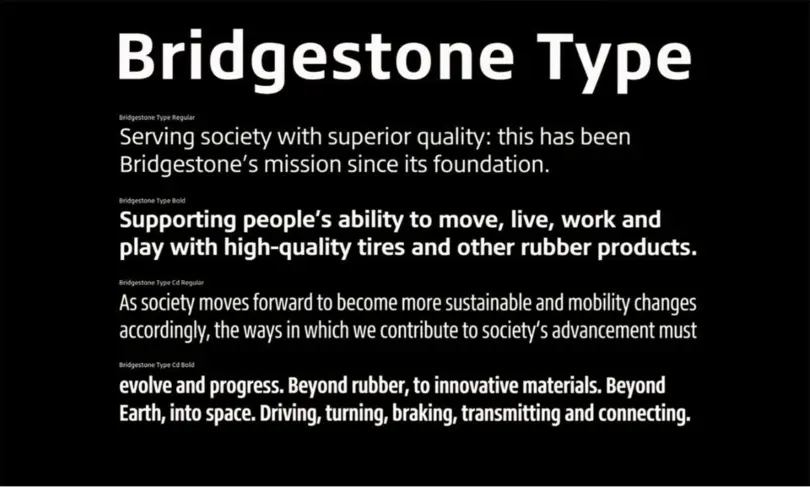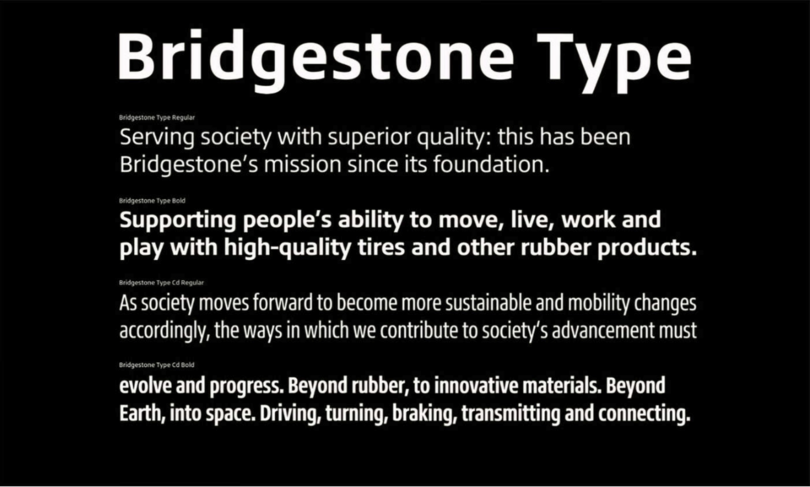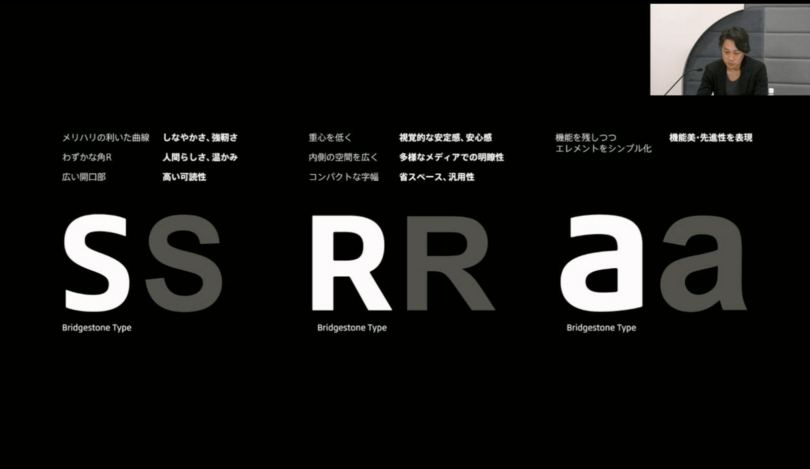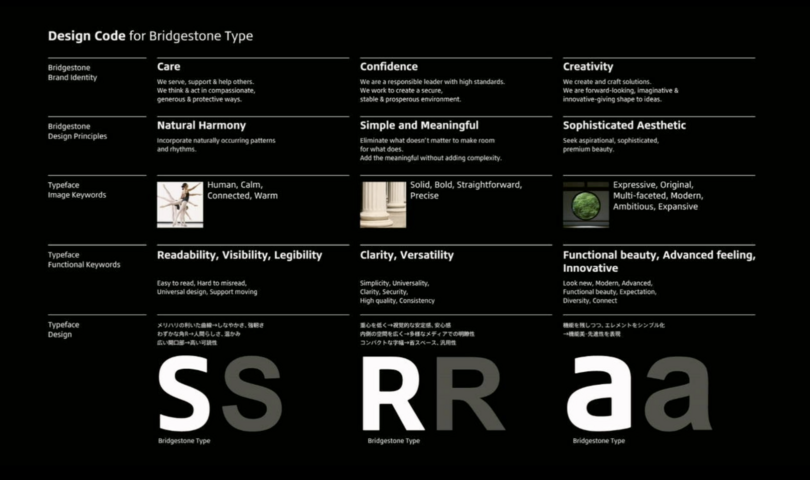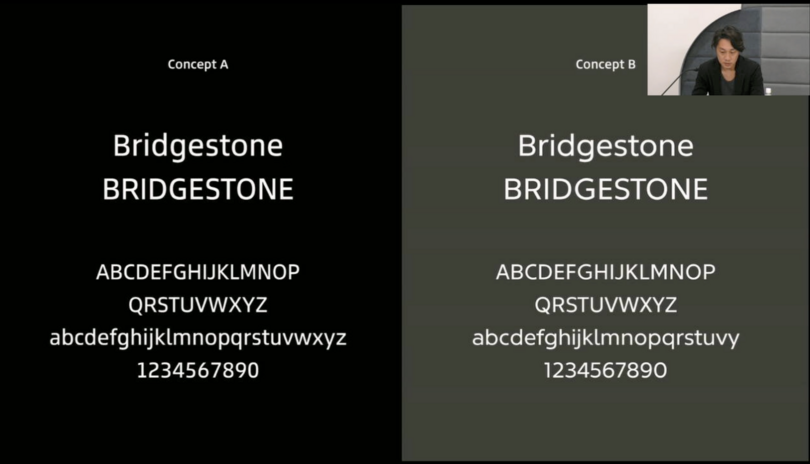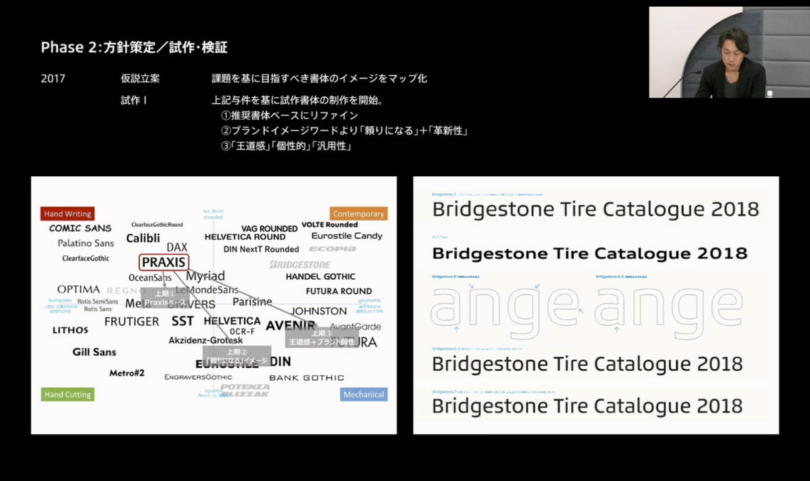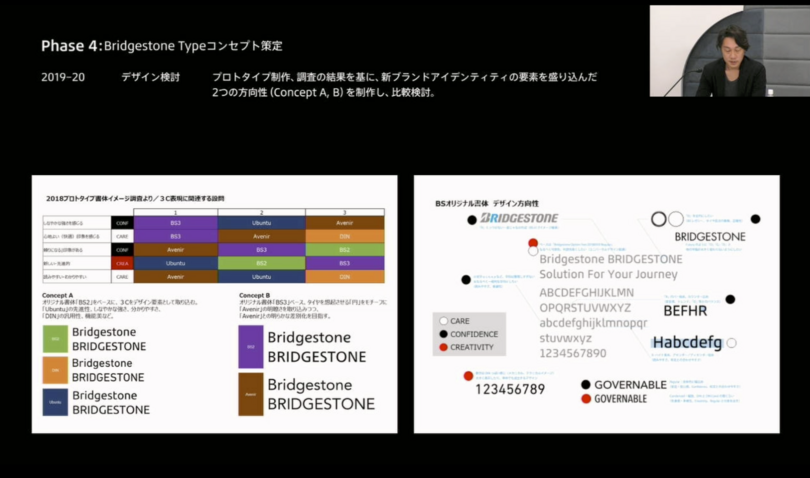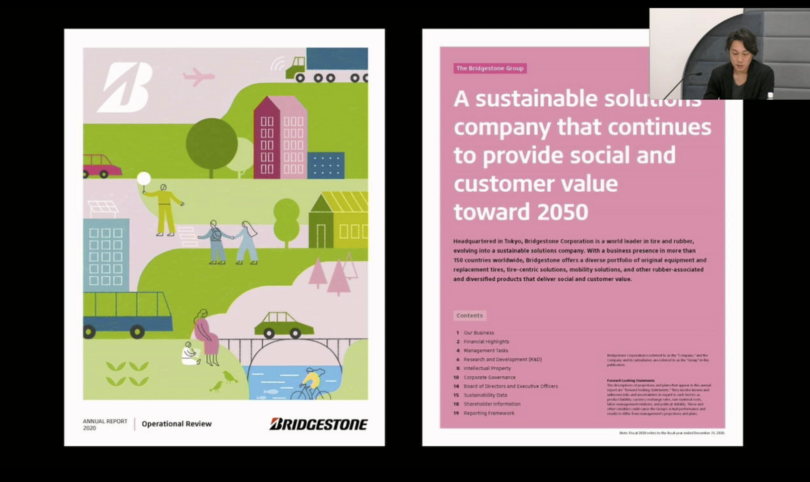
Bridgestone Type
ブランドアイデンティティを反映したコーポレートフォント開発について
Type& 2022 Day 1、Session 1の前半、株式会社ブリヂストン 酒本氏のプレゼンテーションのレポート。ケーススタディよりさらに詳しくコーポレートフォント制作について解説。
Bridgestone Typeについて
酒本氏は、2013年、株式会社ブリヂストンに入社。アートディレクターとしてコーポレートデザイン、デザイン戦略を担当し、現在はコーポレートブランド部門Bridgestone Design部の上席主幹をされています。セッションでは、ブリヂストンのコーポレート書体であるBridgestone Typeについて、書体の特徴や開発経緯についてお話されました。
株式会社ブリヂストンは1931年に設立されたタイヤ・ゴム業界におけるグローバルリーディングカンパニー。コア事業であるタイヤ事業、タイヤ事業の強みを生かしたソリューション事業、免震ゴムやゴルフ用品、自転車などの化工品・多角化事業を展開しています。ブリヂストンらしさを取り入れた書体として、Bridgestone Typeは開発されました。
Regular、Bold、それぞれのコンデンス体。文字全体は四角っぽい形をしていますが、画線には柔らかさを残し、xハイトが高めで、カウンタースペースを広めに取っているのが特徴です。
一番左のSの文字は曲線のメリハリを意識。線の先端がとがらないようにやや丸めています。中央のRは、文字センターの横棒を低めに設定。これにより安心感、安定感が感じられ、カウンタースペースも広く取れるように工夫されています。右側のaは、文字の細部を違和感ない程度に単純化。ブリヂストンの先進性を表現しています。様々なメディア適性を考慮して、可読性、視認性、明瞭性についても配慮しました。
この図はBridgestone Typeを作るための「デザインコード」です。横軸にCare、Confidence、Creativityがあり、縦軸はキーワードやデザイン上の要素。図表の下に行くほど具体的なデザインになるように構成されています。
開発経緯 2019–20
Bridgestone Typeの開発が決定したのは、2019年11月末。小平地区の再開発の中で、サインシステムの再考を提案した際、オプションの一つとして書体開発について言及されました。当時開発していた新しいブランドアイデンティティ(前述の「3つのC」)に合わせた書体を作り、マニュアル化するという指示がありました。2020年3月末に行われるグローバル・エクゼクティブ・コミッティで書体を承認してもらうためには、その1か月前にあるグローバル・ブランド・コミッティでの承認が必要。そこに提出するため、2月はじめに書体のデザイン提案をしなければなりませんでした。つまり、年末年始を除くと書体の検討ができる期間は1ヶ月半くらいしかなかったのです。
この期間でデザインチームは2つの方向性の違う書体、コンセプトAとBを提案。コンセプトAはブランドアイデンティティ(3つのC)を形として取り入れ、先進性を意識。コンセプトBは、ブリヂストンらしい形として円と直線をテーマとして作られた書体で、普遍性を意識しました。
コンセプトAは前述の通りですが、コンセプトBはカウンターの部分にタイヤから着想した円形を取り入れ、できるだけ直線を取り入れた形に。ブリヂストンのBマーク(大文字Bのみをデザインしたブランドマーク)の傾きである16度に合わせて文字の先端も16度に揃え、ブリヂストンらしい形を取り込みました。
書体を決める段階では、3つのCが指標となりました。当時、推奨書体とされていたPraxisは丸みがある書体で、3つのCに当てはめるとCareの要素が強い書体。それに対し、コンセプトAは、Creativityの要素が強く、コンセプトBはConfidenceの要素が強い書体でした。
ブリヂストンは、タイヤメーカーからソリューションカンパニーになるというビジョンを2020年から掲げていました。これまで安心、安全、安定(Confidence)を重視してきたことに加えて、これからはイノベーションやソリューションを表現するようなCreativityが重要になってくると考え、コンセプトAが選ばれました。
プロトタイピング経緯 2014–18
Bridgestone Typeの検討が始まったのは2014年ごろから。開発段階は以下の4つのフェーズに分類されます。
フェーズ1:現状の課題は何かを考え、社内の理解を得るフェーズ
フェーズ2:課題を元に方針を決めて、試作・検証
フェーズ3:実際に書体の意味合いを判断
フェーズ4:それを元に新しい書体に生かす
フェーズ1では、社内への認知、浸透、課題抽出を行いました。デザイン部内でも書体によるブランディングの理解があまり進んでいなかったため、Monotypeの小林章、嘉瑞工房の髙岡昌生氏と一緒に書体の勉強会を実施。社内のブランド部門や広報部門にも声をかけ、社内で勉強会の輪を広げて行きました。当時、国内外のブリヂストンで使われていた欧文書体を集めてみると、グローバルでの書体の使い方が統一されていませんでした。
フェーズ2では、先ほどの課題に対してどう解決していくかを検討。どんな書体を作るのか、左側の図のようにマッピングしながら模索し、3つの方向性を決めました。
- 推奨書体Praxisをベースにリファイン
- ブランドイメージワードから導き出した、「頼りになる」+「革新性」
- 「王道感」「個性的」「汎用性」
ここで作った書体をマップの中に落としこんで、狙い通りにできているかを検証。2回目は以下の方向性で試作しました。
- ブリヂストンロゴをベース
- 「技術力」「先進性」
- 「普遍性」「可読性」
3つ目の評価のフェーズ。
- ブリヂストンロゴとの親和性
- 安定感、先進感、技術力
- 普遍性、可読性、しなやかさ
試作した書体に加え、推奨書体Praxis、既存書体の計9つを、ブリヂストンの拠点がある日本、シンガポール、アメリカ、ヨーロッパの社員に見てもらい、ヒアリングを行いました。ヒアリング結果は集まったものの、この時はブリヂストンらしさが定まっていなかったために正解を選べず、プロジェクトは一旦休止されました。
フェーズ4。再びプロジェクトが動き出したのは2019年11月。それまでに集めた検証結果があったので、書体制作が決まった後はスムーズに進行。3つのCを元に作ったプロトタイプの検証データを元にAとBそれぞれの方向性を定めました。
先進性を取り入れたコンセプトAは、ヨーロッパで使われていたDINや推奨書体として使われていたPraxisの要素を取り入れて調整。一方、普遍性を重視したコンセプトBは、Avenirの明瞭さや信頼感を加えて調整しました。
コンセプトAは、すでに使われていたDINやPraxisに近い字幅で作られているので、書体を切り替える時も比較的スムーズに移行できそうでした。コンセプトBは円の形状を取り入れているため、デザイナーではない一般職からブリヂストンが持つもう一つのグローバルブランド、Firestoneの指定書体であるAvenirとの差が分かりにくいということでした。最終的にコンセプトAが選ばれ、デザインを調整。Bridgestone Typeが完成しました。
使用事例
現在、Bridgestone Typeはグローバルでブリヂストンを表現する書体として、様々な用途で幅広く活用されています。
ブリヂストン・イノベーション・パーク内の施設であるブリヂストン・イノベーション・ギャラリーで使用
アニュアルレポート - タイポグラフィをメインにする使い方や本文の文字組みにも対応。Bridgestone Typeを作る際には、サインのような大きい文字から本文やキャプションのように小さい文字まで使えるよう、汎用性の高い書体を目指した。
総合報告書2022。和文欧文を併記したサンプル。和文書体にはタイププロジェクトのAXIS Fontのフィットフォントを使用。Bridgestone Typeに合わせて、和文フォントのウェイトを調整。